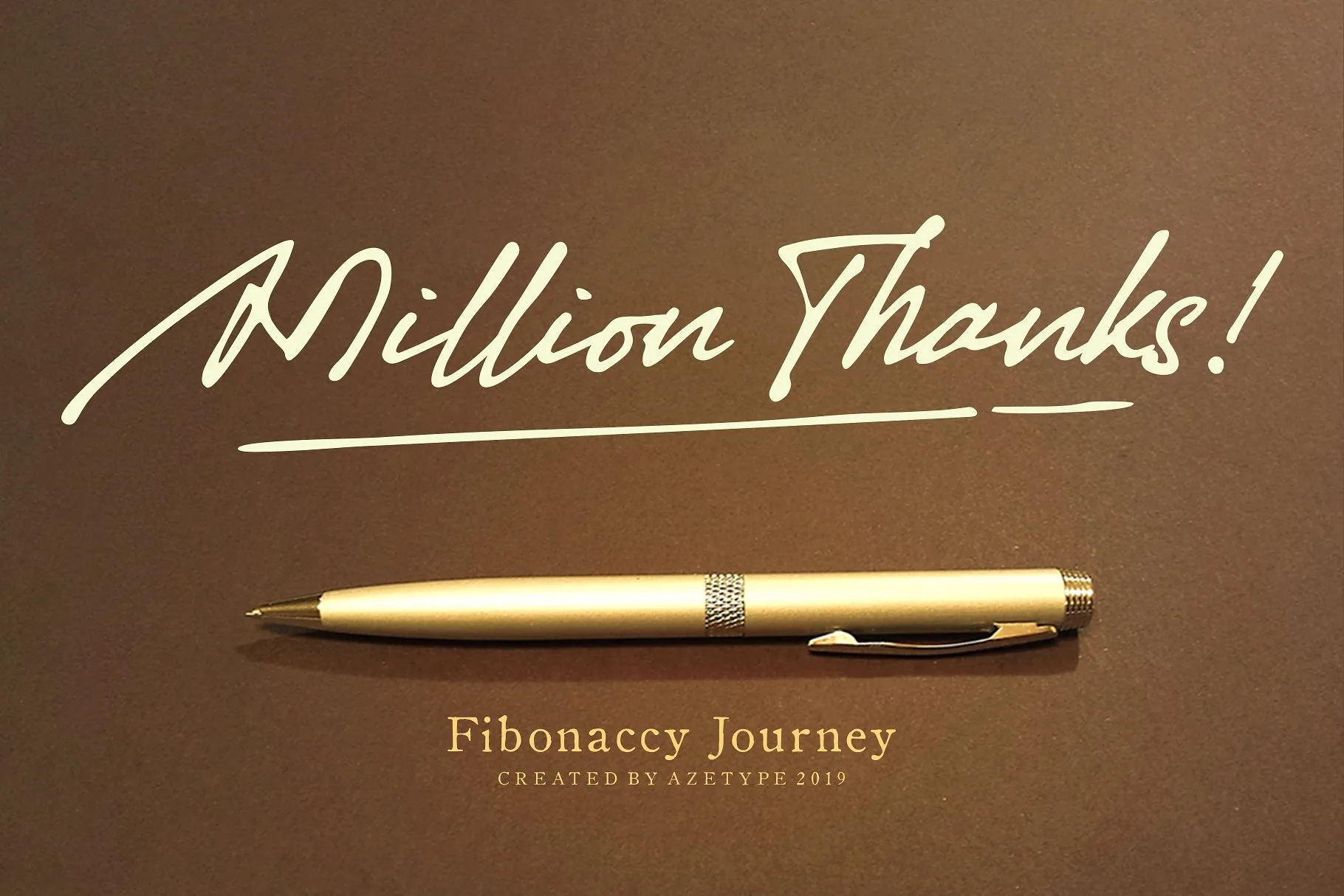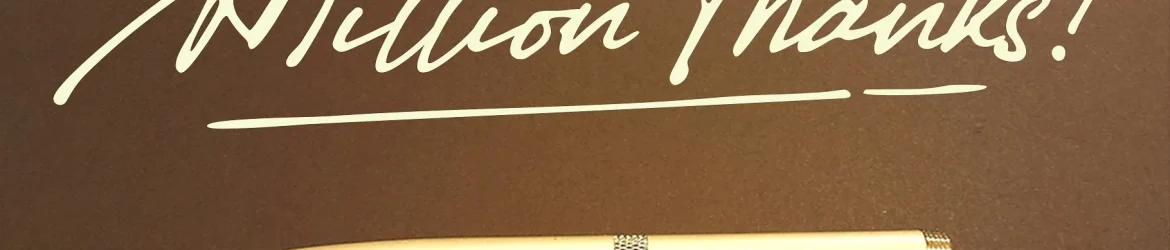
Fibonaccy Journey Script Font – Download Grátis
Esta é uma especialização única de script com toque de textura de traço de tinta escrita à mão. Também tem uma estética de citação única. Introduzimos a Fibonaccy Journey Font, um tipo manuscrito meticulosamente criado. Fundido com originalas marcações digitais feitas à mão que exibem elegância e estilo vintage. Este tipo pode ser usado em qualquer momento e em qualquer projeto. Como você pode ver na imagem de apresentação acima, perceberá como ela funciona!